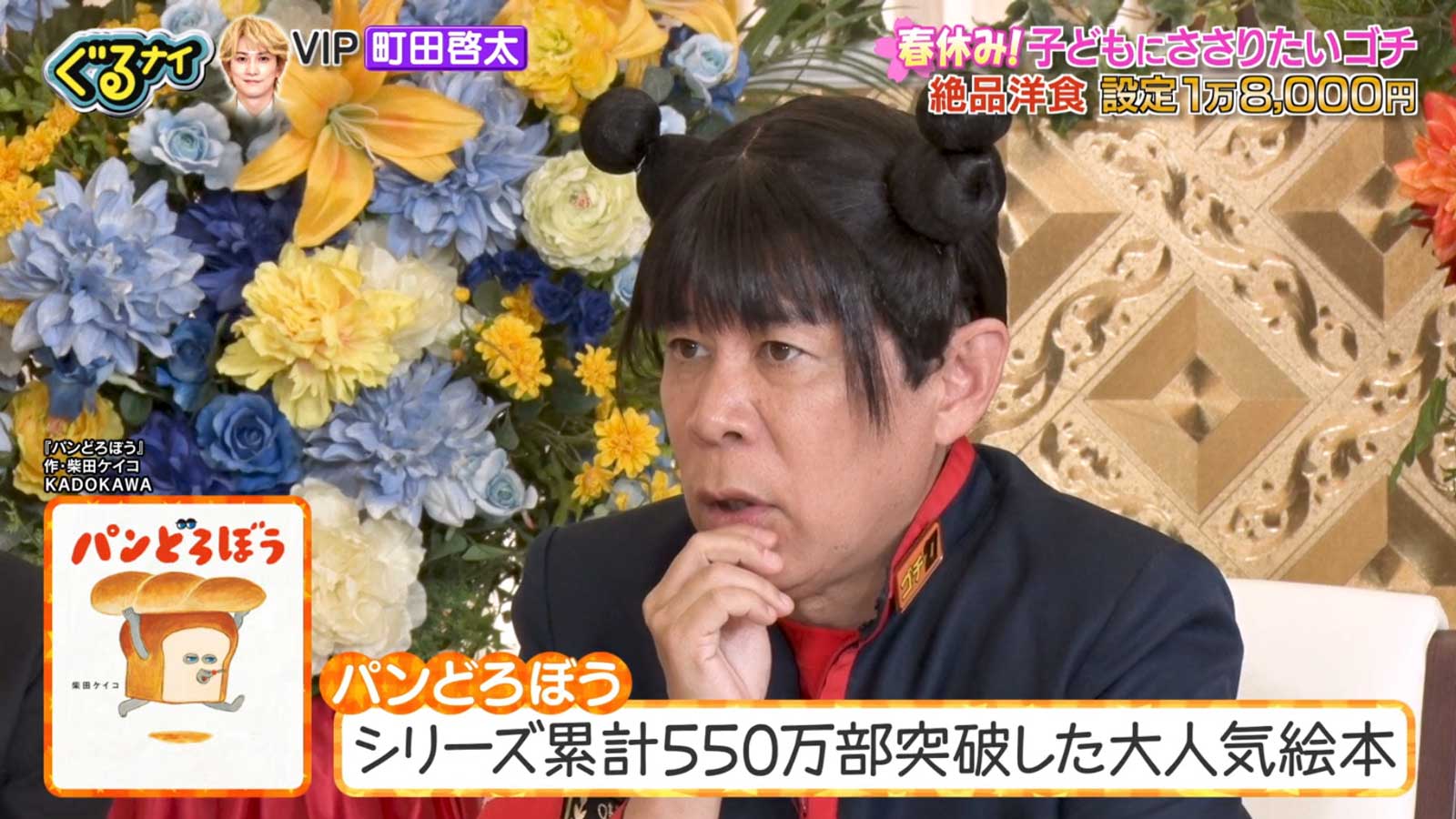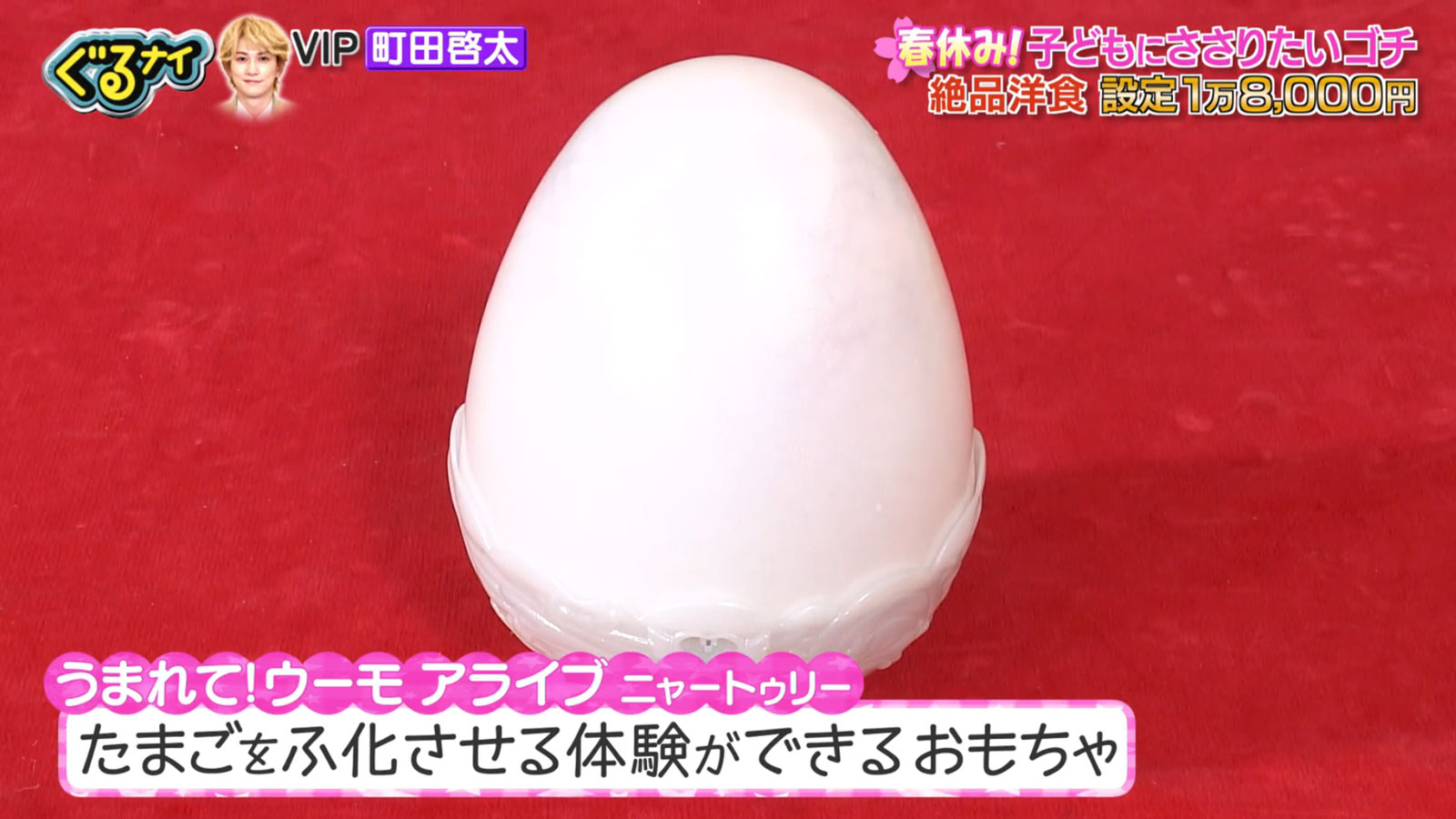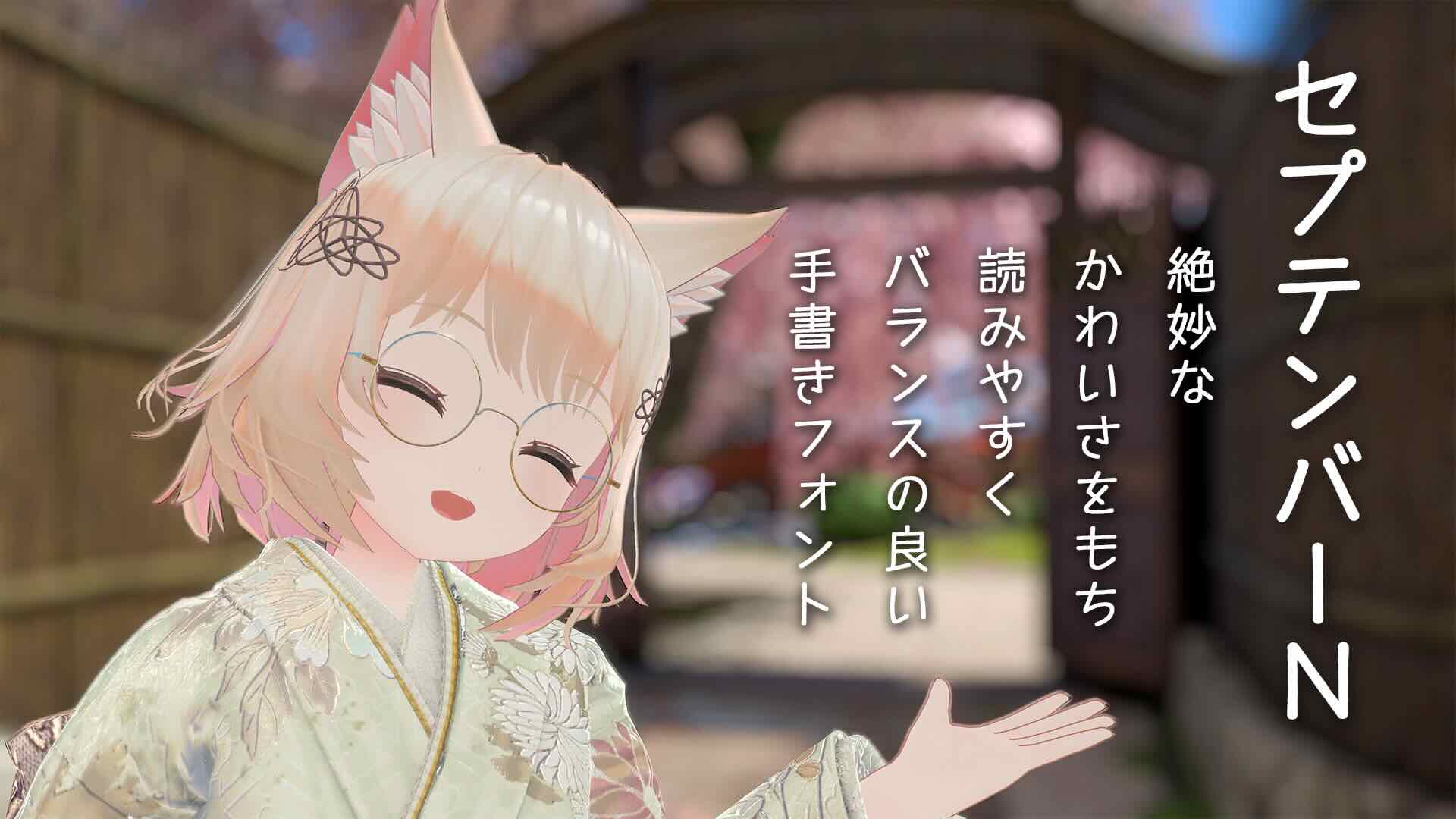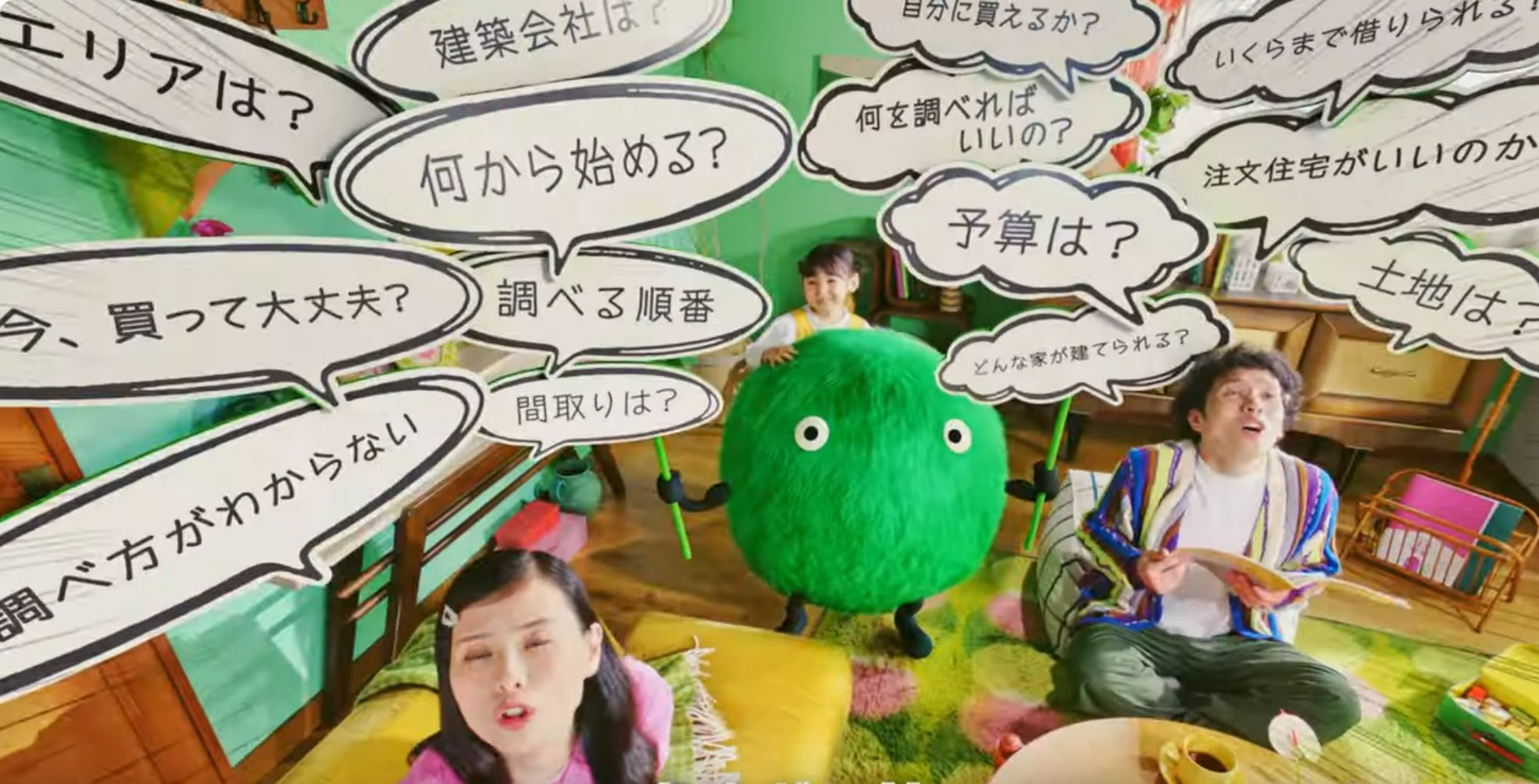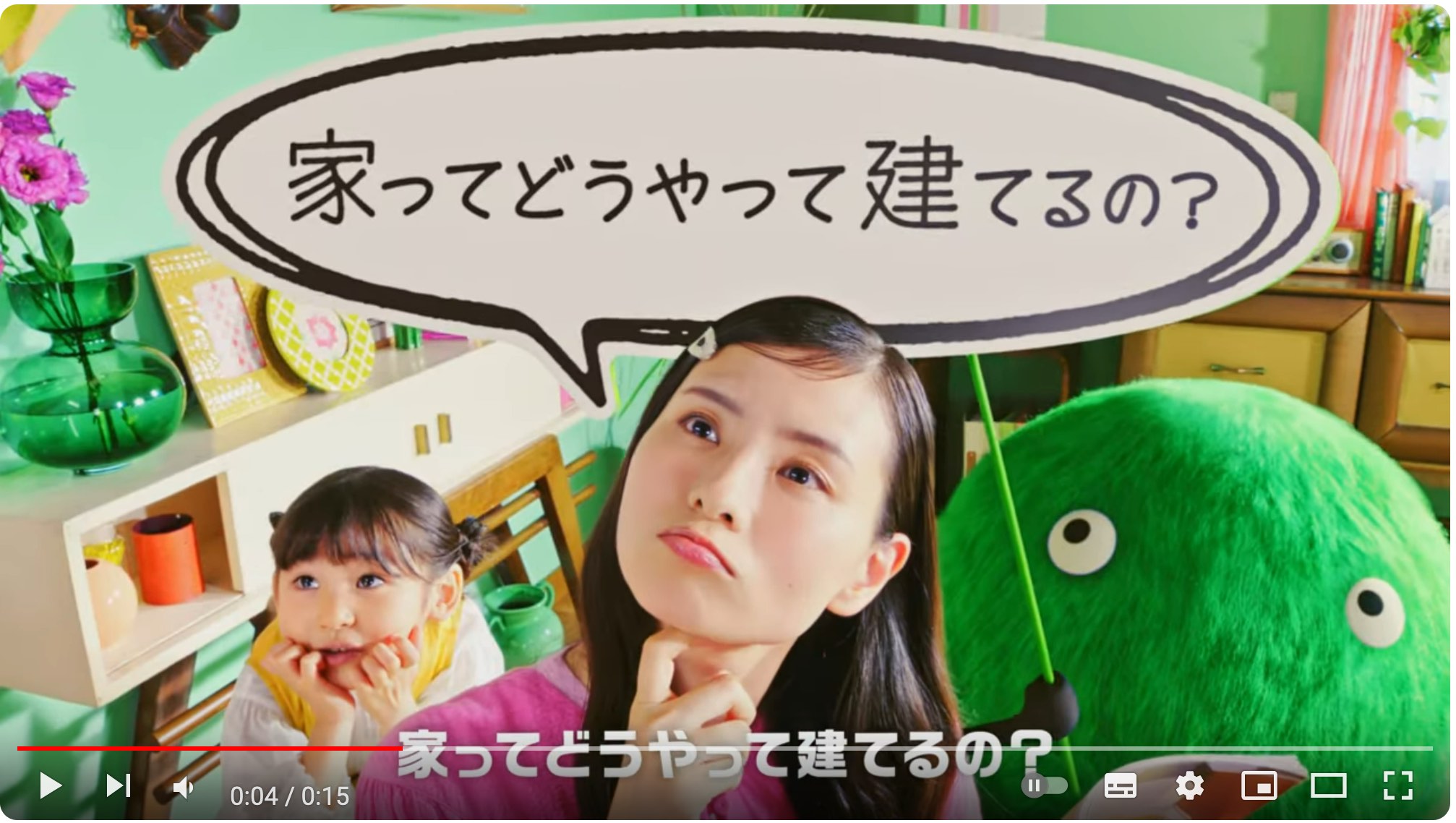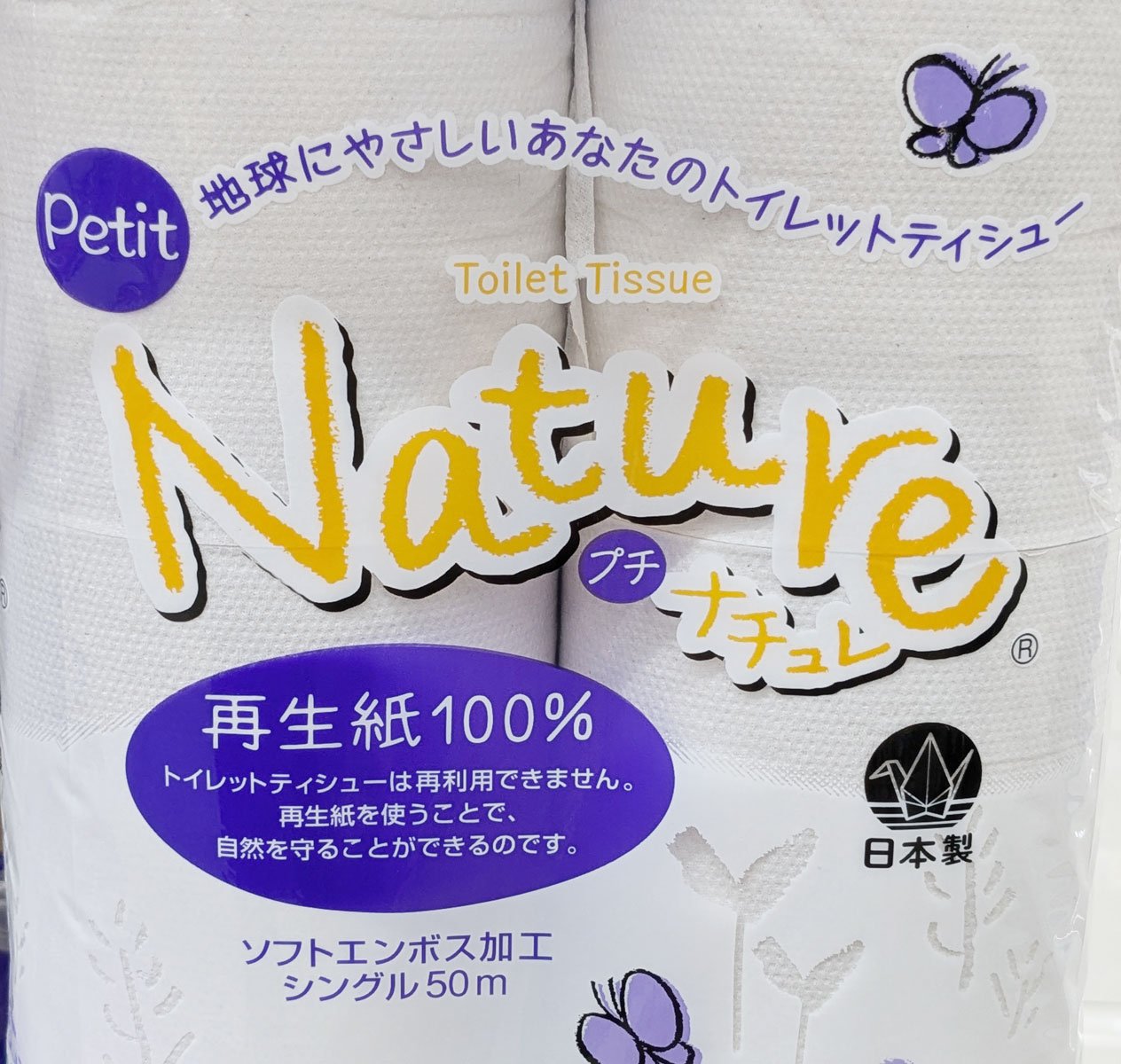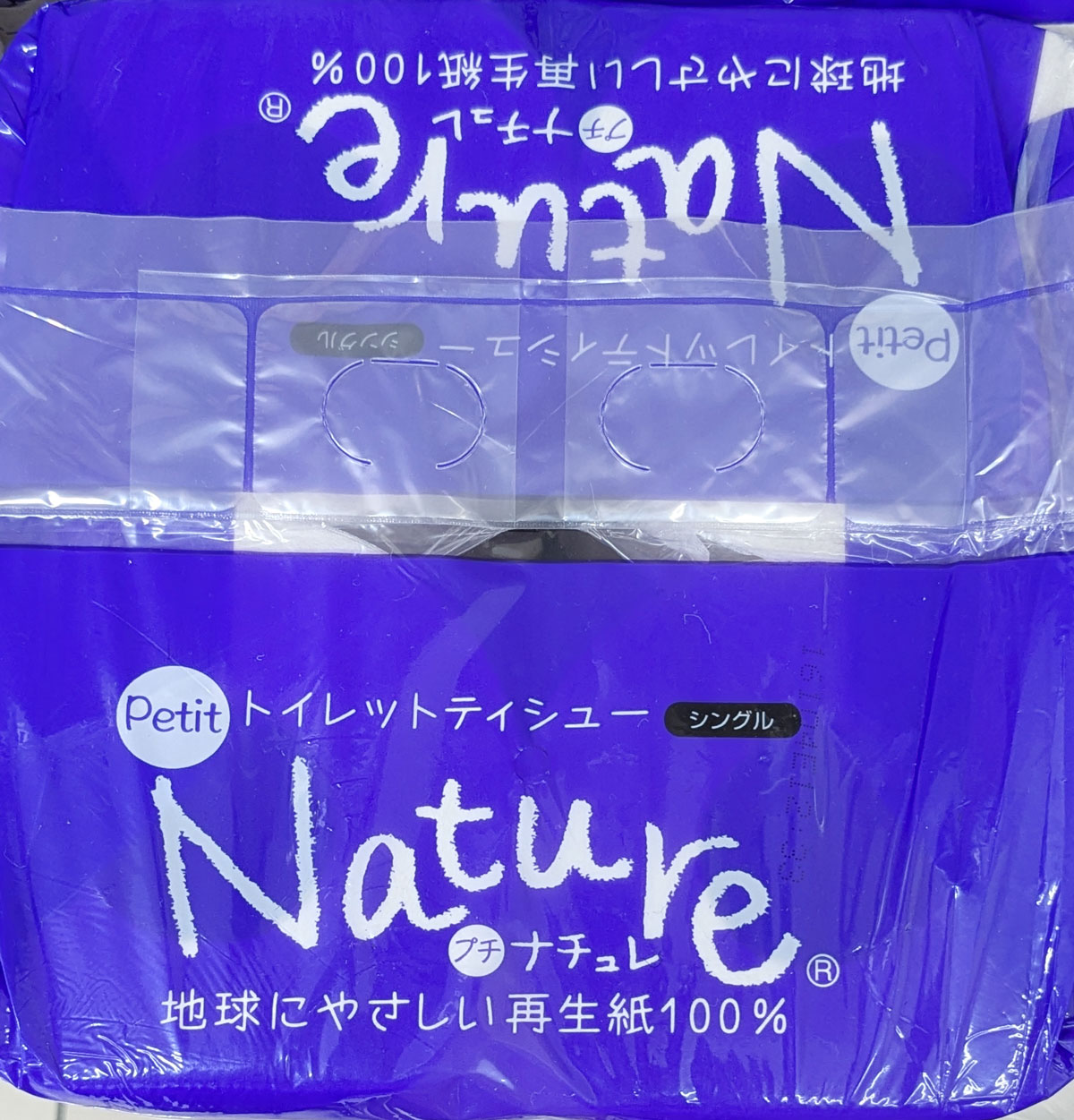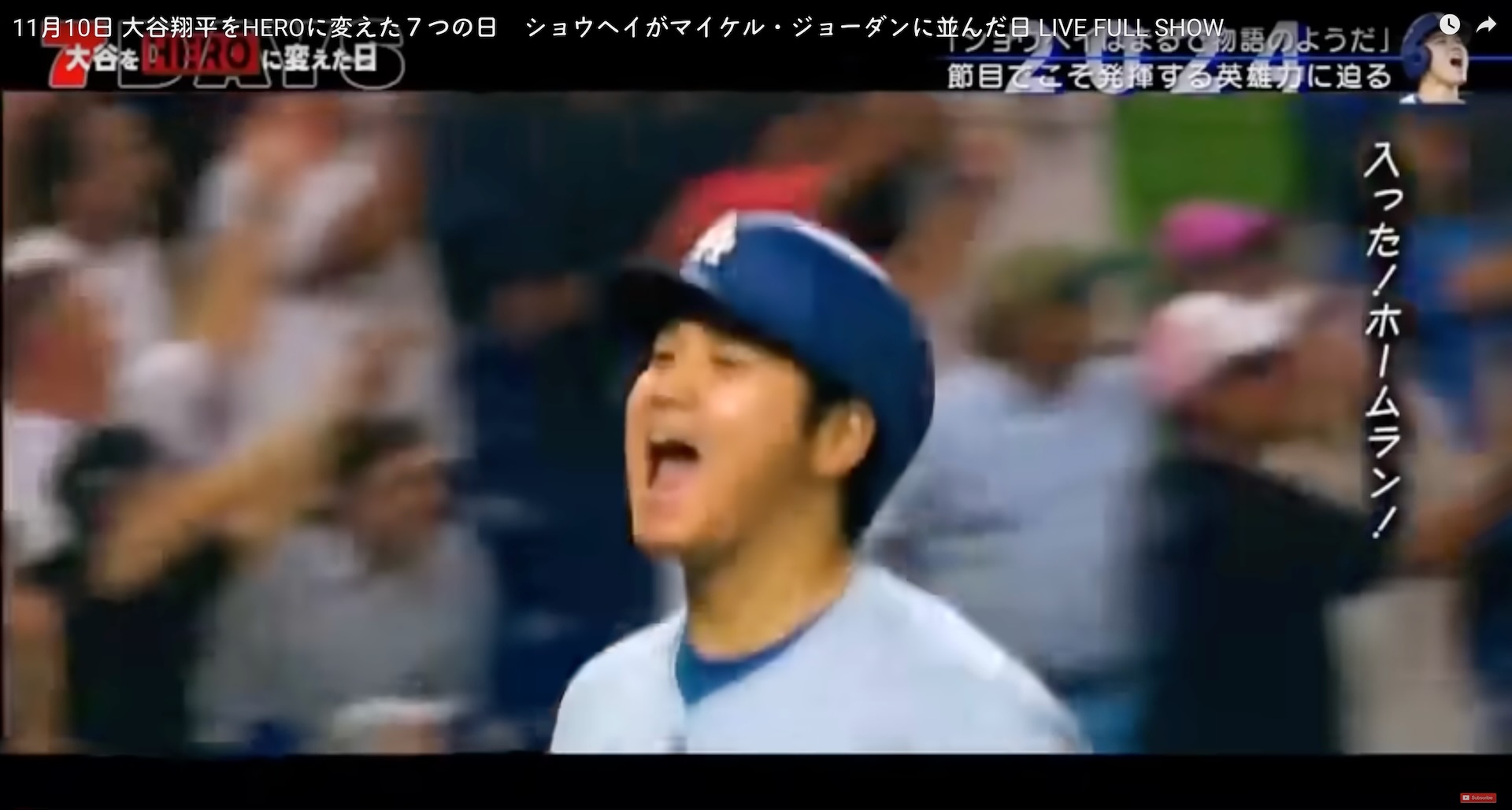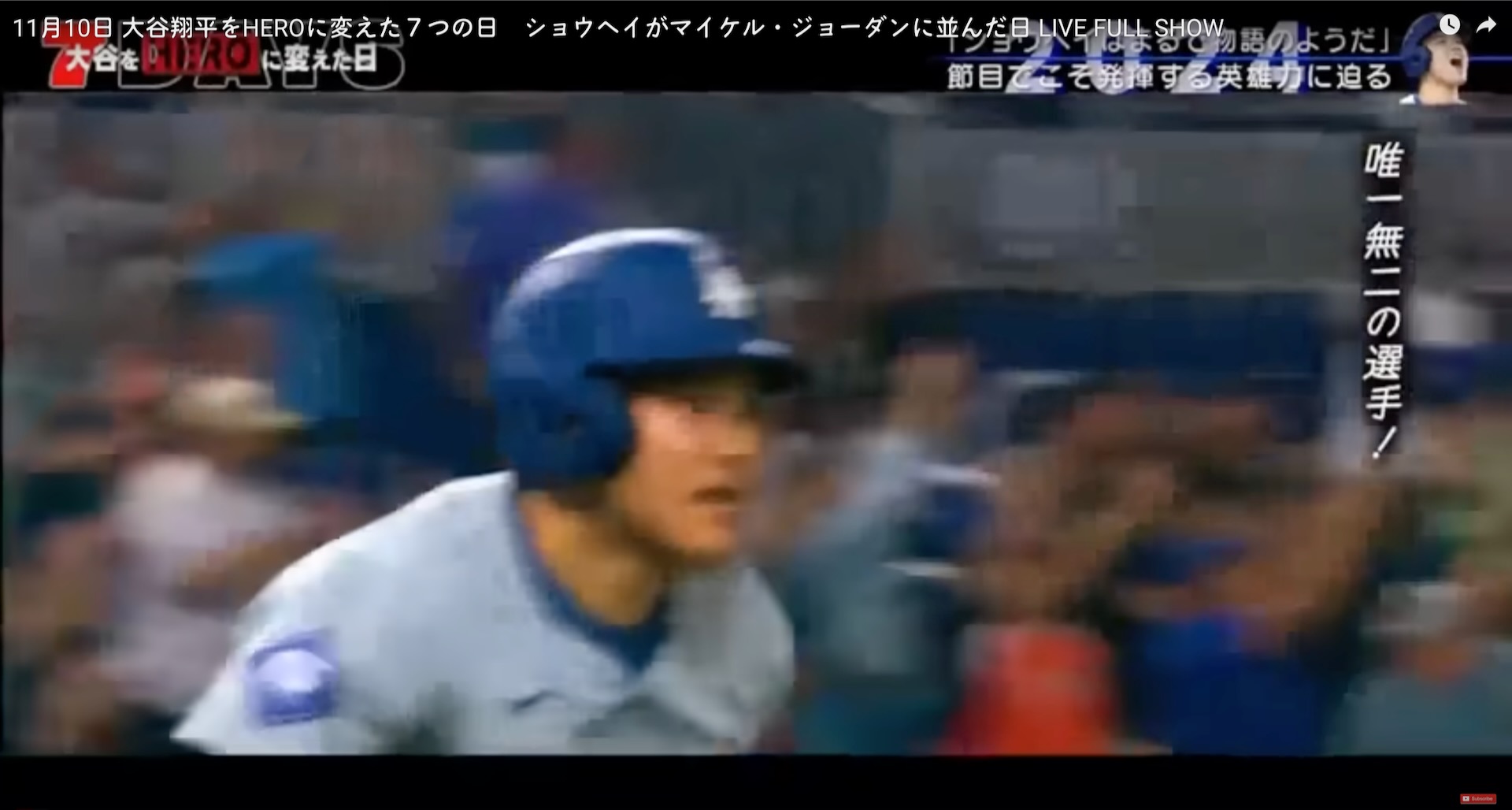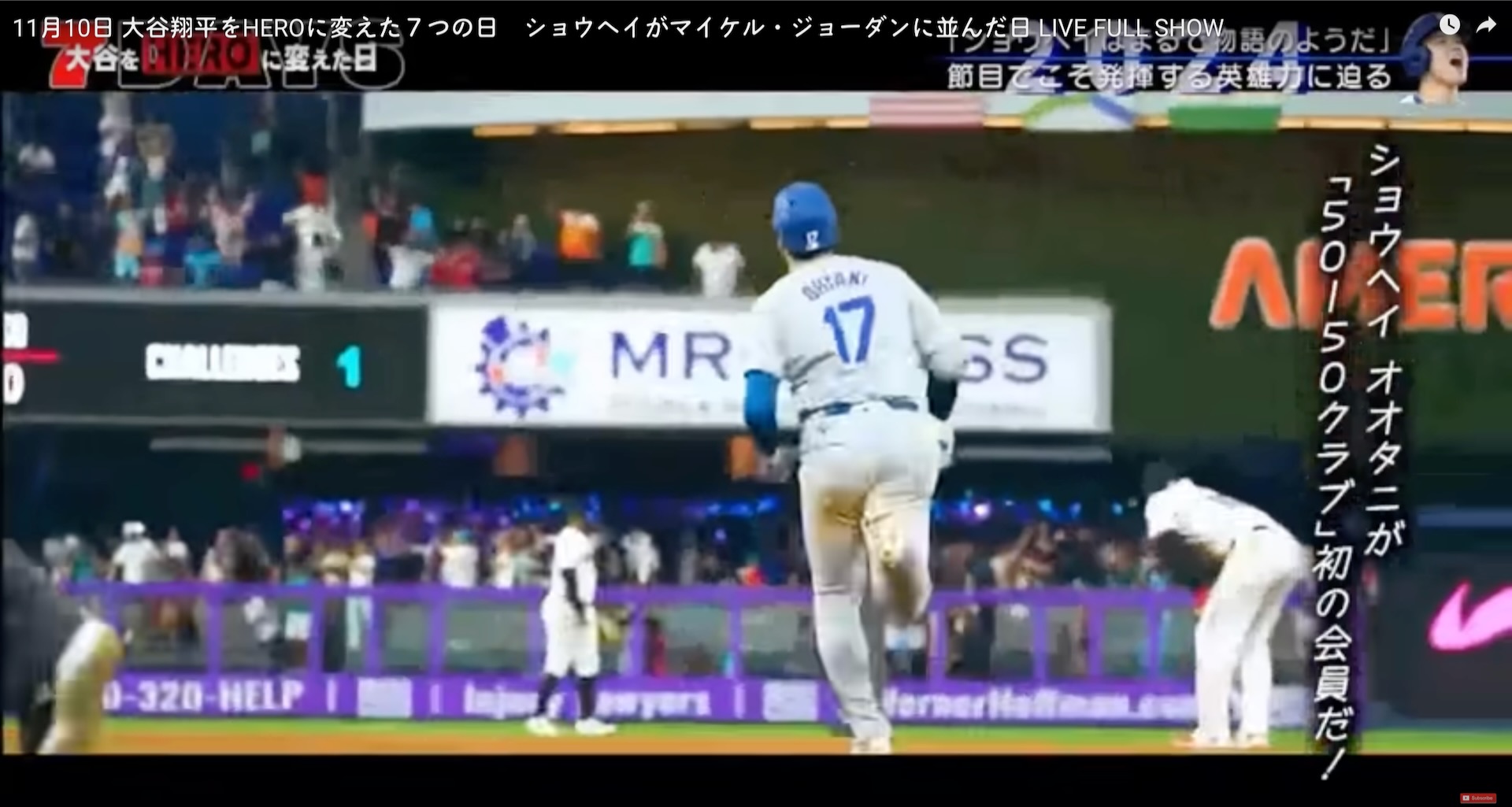
サムネール画像 さとうゆたか
Vアニメ『スローループ』エンディングテーマ。
Three∞Loop 「シュワシュワ」Music Video。
ショップチャンネル takumi
ショップチャンネルの「お客様の声」のパネルで使われていたセプテンバー書体です。
もう1枚。
セプテンバー書体の使用例は、なかなか見つけられませんので、貴重です!
バランスの良い手書きフォント さとうゆたか
りぶにゃんという方が、X(旧Twitter)で紹介してくれている。
本の表紙 さとうゆたか
書名:絵かき猫マヌーのスケッチブック
著者:横山ゴロー
発行:主婦と生活社
しかし、なんで「ッ」をこんなに小さく加工するかね…。
「ブ」の濁点も正規のものと違うようだ…。
あ…、そういう事情なのかな…。
「ぐるナイ」にて takumi
日本テレビの「ぐるぐるナインティナイン」でのセプテンバーN使用例です。
この番組はLETSに追加された新書体をすぐに採用する傾向があるので、LETSからのチョイスかと思います。
これも。
LETSでしょうねぇ。
この書体が、今後もっとたくさん使われてくれることを願っております。
BSよしもとの番組 takumi
BSよしもとの番組「つまみは紅しょうが」で使われているセプテンバーフォントです。
これも。
使用例が見つかりにくい書体ですので、助かります。
体育祭の掲示板 セプファン
京都の私立の体育祭で使われていた掲示板。
セプテンバーフォントです。
小さくて見えづらいので、勝手ながら拡大させていただきました…。
正式な画像も掲載させていただきます。
コミックエッセイ さとうゆたか
加鳥アサさんがnoteで描いているコミックエッセイで使われてます。
コミックの部分は、こんな感じ…。
本の表紙 takumi
「セプテンバー」フォントが使われた本の表紙です。
これも同じシリーズのようです。
この本、毎月発行されるんですかね…。